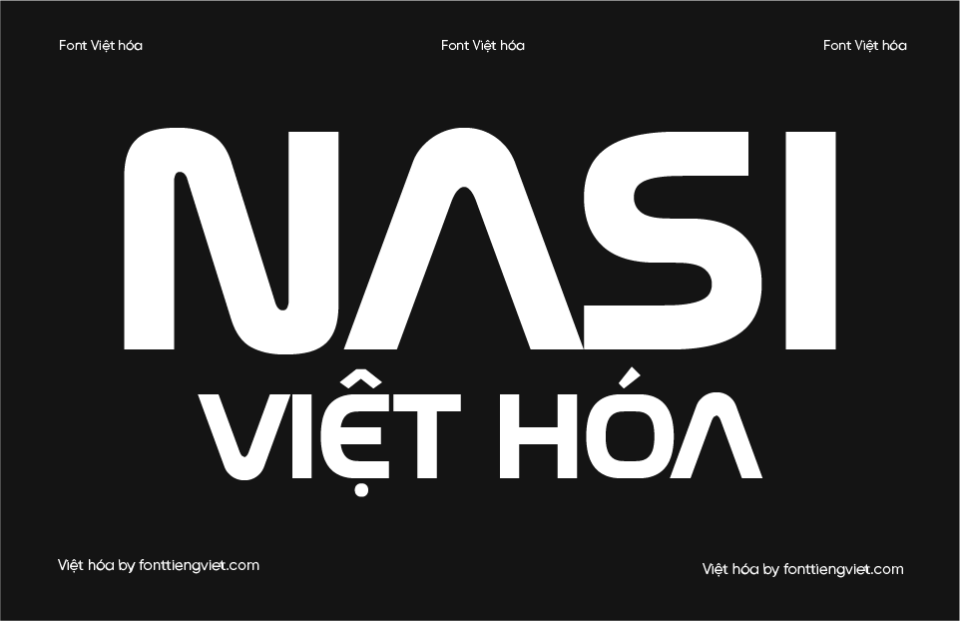
Giới thiệu về Font Việt hóa 1FTV Nasi
Trong thế giới thiết kế đồ họa hiện đại, việc tìm kiếm một Font Chữ vừa mang nét truyền thống vừa mang hơi thở đương đại là điều không hề dễ dàng. Font Việt hóa 1FTV Nasi nổi lên như một sự lựa chọn hàng đầu cho các nhà thiết kế muốn tạo điểm nhấn độc đáo cho dự án của mình. Đây là bộ phông chữ được tối ưu hóa hoàn toàn cho tiếng Việt, giúp người dùng không còn lo lắng về lỗi hiển thị dấu hay khoảng cách ký tự. Với phong cách thanh lịch và mạnh mẽ, bộ phông này đặc biệt phù hợp cho các em học sinh, sinh viên và giáo viên trong việc làm slide bài giảng hoặc báo cáo sáng tạo.
Những đặc điểm nổi bật của Font Việt hóa 1FTV Nasi
Thiết kế linh hoạt và đa dụng
Font Việt hóa 1FTV Nasi sở hữu các đường nét tinh tế, dễ đọc nhưng vẫn giữ được cá tính riêng biệt. Các ký tự được điều chỉnh thủ công để đảm bảo sự cân đối tuyệt đối khi đứng cạnh nhau. Bạn có thể sử dụng bộ font này cho nhiều mục đích khác nhau như thiết kế poster sự kiện trường học, bìa sách, hay thậm chí là các ấn phẩm truyền thông trên mạng xã hội. Sự đa dạng trong phong cách giúp nó thích nghi tốt với cả nền tối và sáng.
Lời kết và hướng dẫn sử dụng